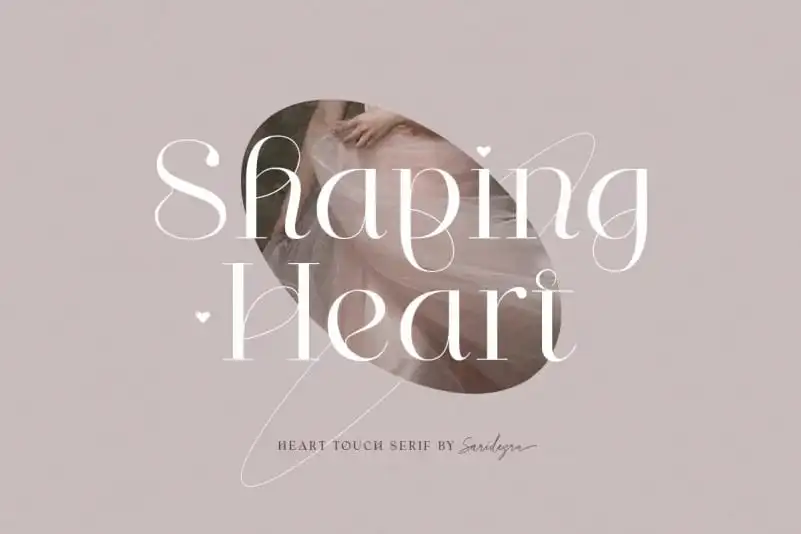
Shaping Heart Serif Font – Download Grátis
A Shaping Heart Serif Font é uma escolha incrível para quem busca uma aparência elegante e sofisticada. Feita pelo designer Sarid Ezra, essa serif font apresenta uma versão condensada que se destaca tanto nos caracteres maiúsculos quanto nos minúsculos. Ideal não só para as iniciais de casamento ou o seu próprio estandarte, também pode ser usada em diversos contextos, como por exemplo para criar logotipos únicos e criativos. Além disso, a Shaping Heart Serif é uma fonte multi-língue que já vem codificada com PUA (Pre-Composed Unicode Area), o que permite maior flexibilidade ao trabalhar em projetos que exijam várias idiomas. Sua rica detalhismo torna-a ainda mais atraente, oferecendo um toque extra de sofisticação e personalidade aos seus materiais gráficos. Esta fonte é certamente uma excelente escolha para quem valoriza tanto o estilo quanto a funcionalidade em seu próximo projeto visual.